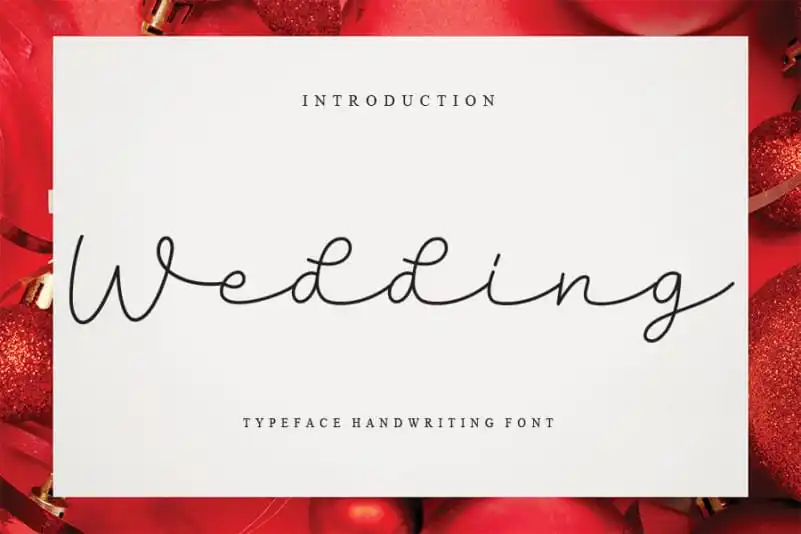
Wedding Script Font – Download Grátis
Nossa fonte Wedding Script Font é a escolha perfeita para criadores de conteúdo que buscam uma aparição autêntica e elaborada. Desenvolvida pelo designer creativeletter, ela oferece um toque elegante e personalizado ao seu trabalho. Seja você um fotógrafo de casamento ou simplesmente alguém que deseja dar um toque especial à sua arte digital, esta fonte é perfeita para criar imagens memoráveis e emotivas. Os seus traços cuidadosos e estilo retrô proporcionam um ar artesanal sem igual. Seja no design de logotipos, cartazes ou em qualquer outra forma de arte digitais que você tenha em mente, esta fonte é uma maneira incrível de transmitir sentimentos sutis através do design. Experimente a Wedding Script Font e transforme sua experiência criativa em algo único e memorável.